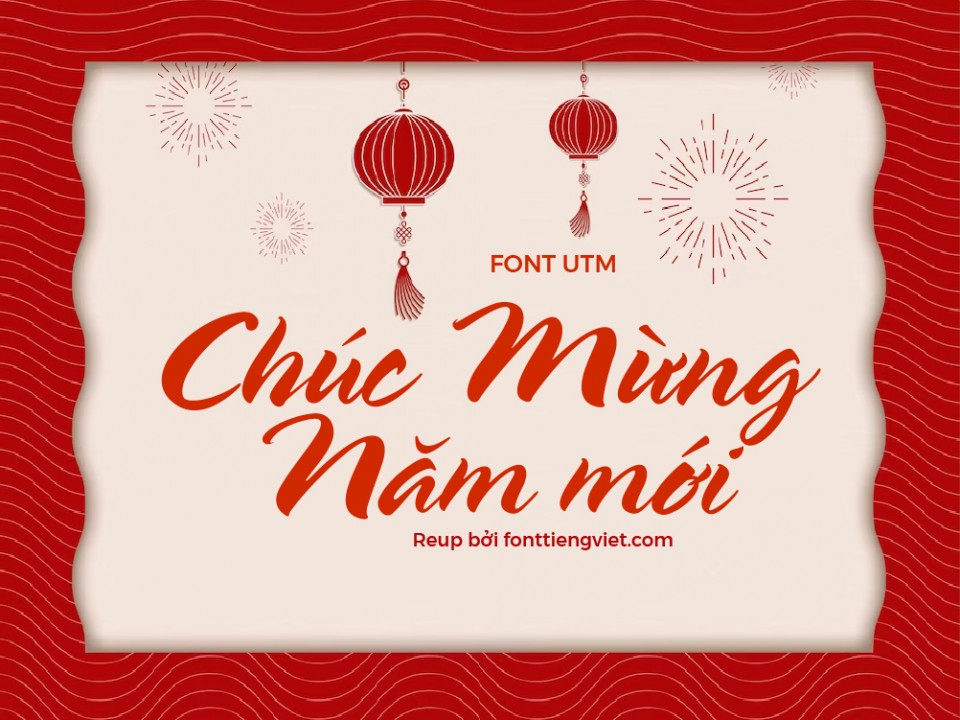
Font việt hóa UTM Spring – Tết
Font việt hóa UTM Spring – Tết – Lựa chọn hoàn hảo cho thiết kế Xuân rực rỡ
Giới thiệu về Font việt hóa UTM Spring – Tết
Chào đón không khí rộn ràng của những ngày đầu năm, việc lựa chọn một Font Miễn Phí phù hợp là yếu tố then chốt để tạo nên những ấn tượng thị giác mạnh mẽ. Trong số các bộ phông chữ nổi bật, Font việt hóa UTM Spring – Tết luôn được các nhà thiết kế tại Việt Nam ưu tiên lựa chọn. Đây là một phông chữ mang đậm nét văn hóa truyền thống, sự kết hợp tinh tế giữa nét chữ viết tay mềm mại và cấu trúc hiện đại, giúp truyền tải thông điệp chúc mừng năm mới một cách chân thành nhất.
Ưu điểm nổi bật của bộ Font việt hóa UTM Spring – Tết
Đặc điểm lớn nhất của Font việt hóa UTM Spring – Tết chính là khả năng hiển thị tiếng Việt hoàn hảo, không bị lỗi dấu, một vấn đề thường gặp ở các phông chữ quốc tế. Phông chữ này sở hữu các đường nét thanh mảnh nhưng chắc chắn, gợi lên hình ảnh của những nhành mai, nhành đào đang đua nhau khoe sắc. Ngoài ra, tính ứng dụng của nó cực kỳ cao, từ việc thiết kế thiệp chúc mừng, banner quảng cáo sự kiện đến các ấn phẩm truyền thông học đường, giúp học sinh và giáo viên dễ dàng tạo ra những tác phẩm đẹp mắt.
Cách ứng dụng Font việt hóa UTM Spring – Tết hiệu quả
Để tận dụng tối đa vẻ đẹp của bộ chữ này, bạn nên kết hợp với các gam màu nóng như đỏ, vàng hoặc xanh lá cây để làm nổi bật chủ đề ngày Tết. Font việt hóa UTM Spring – Tết hoạt động tốt nhất khi được dùng làm tiêu đề chính hoặc các câu đối ngắn gọn. Bạn không nên sử dụng phông chữ này cho các đoạn văn bản dài vì tính nghệ thuật cao có thể gây mỏi mắt cho người đọc. Thay vào đó, hãy biến nó thành điểm nhấn nghệ thuật trên các bìa báo tường hoặc thiệp mời họp mặt đầu xuân của nhà trường.